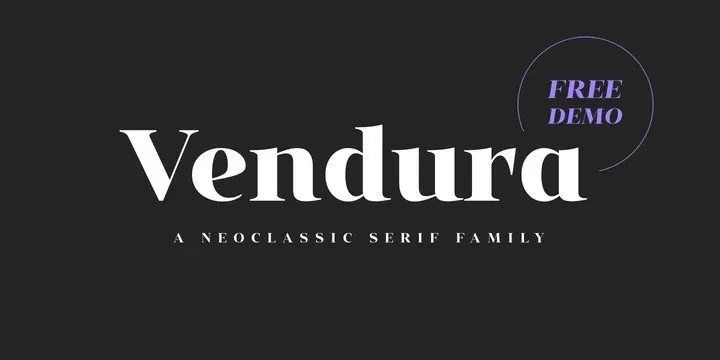
Vendura Sans Serif é uma fonte elegante e versátil, perfeitamente adaptada para diversos usos, especialmente aplicações de títulos e pequenos pedaços de texto tanto em impressão quanto na internet. Essa família tipo lembra as famílias serifadas modernas do século XVIII e XIX, conhecidas por sua contraste alto entre linhas e espaçamento. Vendura traz um toque moderno a essa estética clássica, adicionando detalhes únicos que dão ao conjunto uma aparência mais atual. Esta fonte adorna projetos de design editorial, identidades corporativas e interfaces de usuário com muito personalidade. Com sete pesos diferentes, Vendura apresenta bordas aguçadas e pontilhadas, criando um aspecto suave e acolhedor que contrasta a rigidez da serifada. Ideal para criar uma identidade visual única e moderna em qualquer projeto de design digital ou impressão.